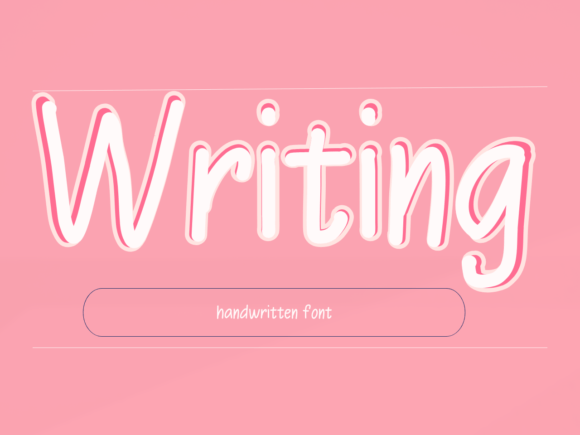
Writing
Ulasan Lengkap tentang Font “Writing” – Pilihan Terbaik untuk Logo, Branding, dan Kutipan
Jika Anda sedang mencari font handwritten yang elegan, modern, dan tetap memiliki sentuhan klasik, Writing adalah jawabannya. Dirancang dengan detail yang menawan, font ini bukan sekadar huruf – ia memberikan karakter unik pada setiap proyek desain Anda.
- Desain yang Timeless – Setiap huruf pada Writing memiliki bentuk yang natural dan tidak lekang oleh waktu, menjadikannya cocok untuk brand yang ingin tampil abadi.
- Ideal untuk Logo & Branding – Garis-garis halus dan lekuk yang organik membantu menciptakan identitas visual yang kuat dan mudah diingat.
- Perfect for Quotes – Kesan personal dan hangat dari gaya tulisan tangan membuat kutipan Anda terasa lebih hidup dan menginspirasi.
- Keterbacaan Tinggi – Meskipun memiliki gaya artistik, Writing tetap mudah dibaca pada ukuran kecil hingga besar, sehingga fleksibel untuk berbagai media.
Dengan Writing, setiap huruf membawa sentuhan personal yang akan membuat desain Anda berbicara. Baik untuk startup yang ingin menonjolkan kreativitas, agensi yang membutuhkan identitas visual yang kuat, atau sekadar menambahkan keindahan pada poster kutipan, font ini adalah pilihan yang tak boleh dilewatkan.